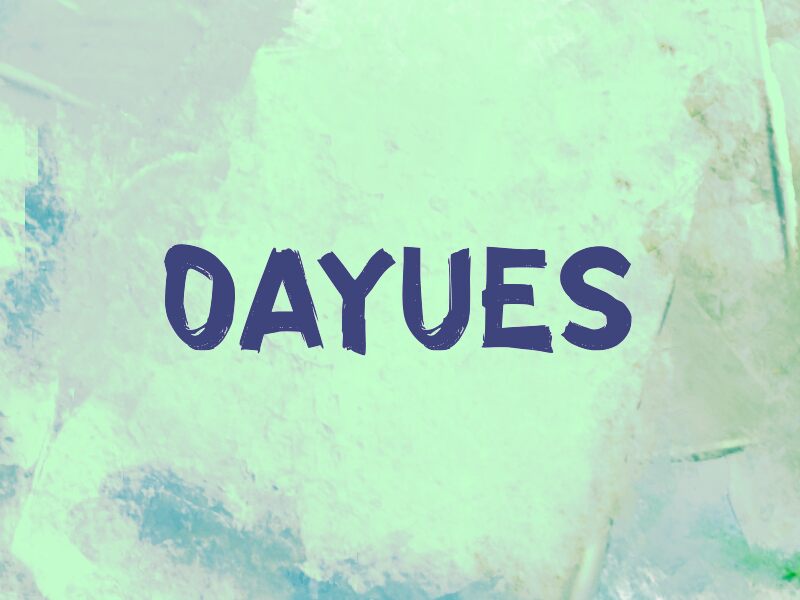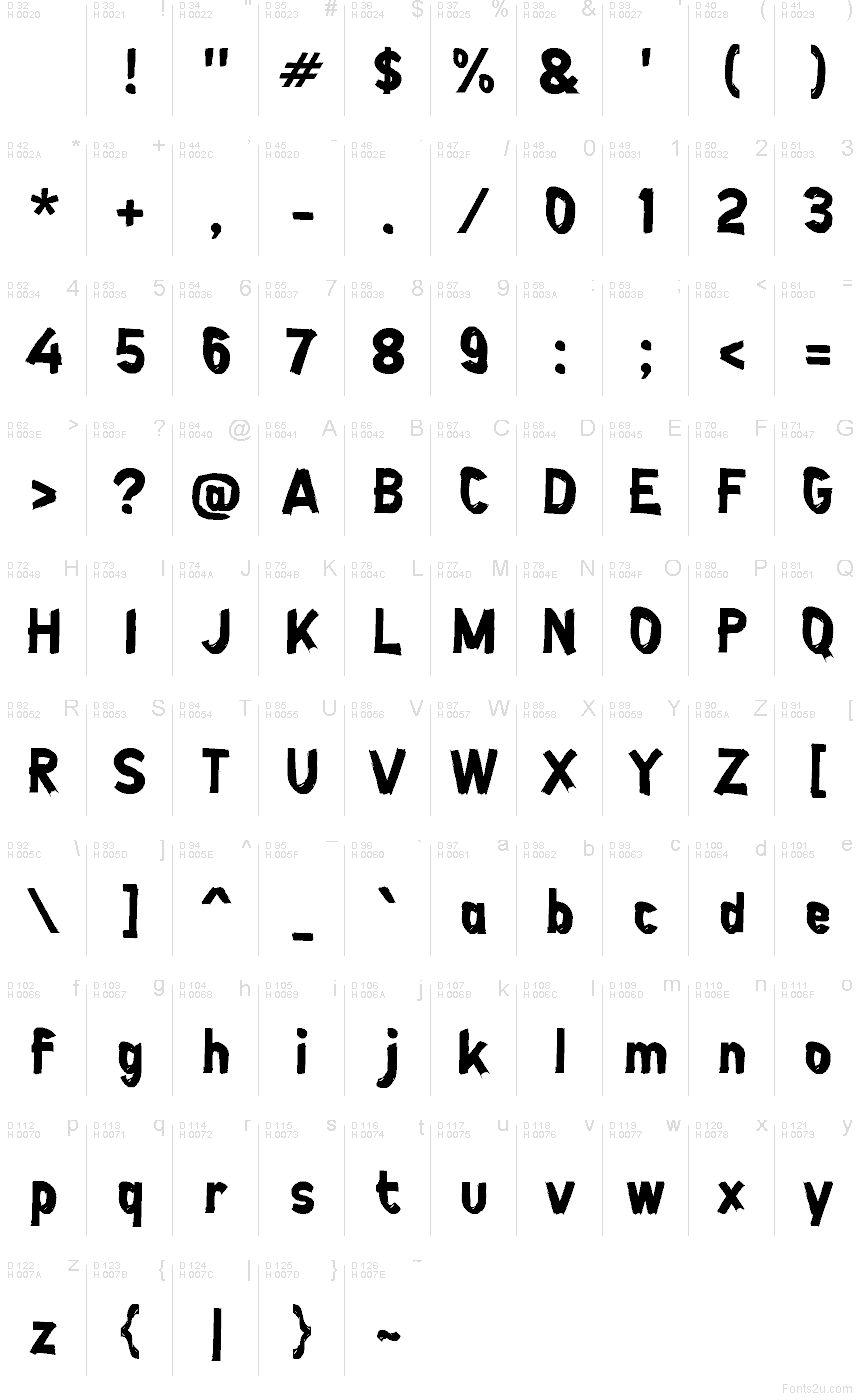
OAYUES
OAYUES de Wep es una tipografía display de estilo pincel gratuita, definida por su textura de trazo seco y bordes irregulares. Sus letras mantienen una presencia sólida y vertical, pero gracias a sus interiores desgastados y acabados deshilachados, evita cualquier sensación de suavizado digital.
Esta textura cruda aporta mucha fuerza a titulares breves, ideal para carteles musicales, diseños de streetwear, packaging, promociones de eventos y contenido en redes sociales que busque un acabado artesanal. OAYUES también destaca en rótulos y etiquetas de merchandising, donde la textura ancha del pincel sostiene el diseño por sí sola sin necesidad de decoraciones extras.